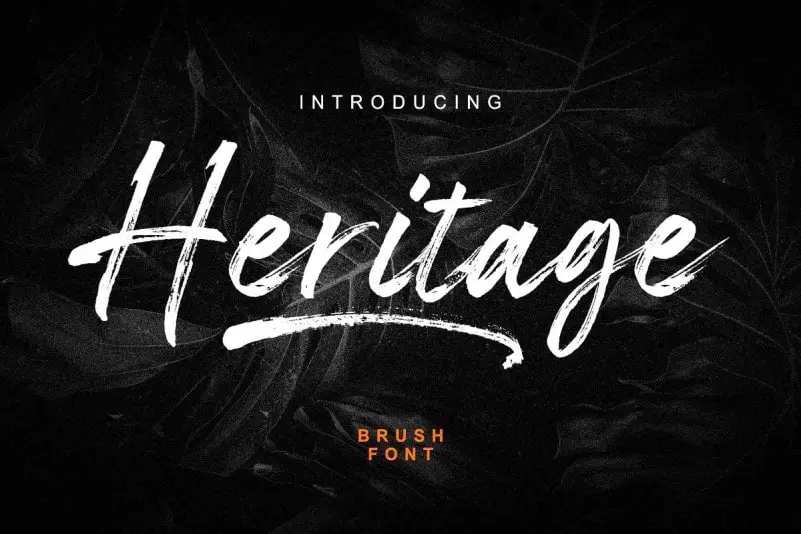
Heritage Brush Font – Download Grátis
A Heritage Brush Font é uma elegante tipografia escrita a mão que combina a facilidade dos traços de uma caneta com as curvas naturais e suavidades do estilo à mão. Seu design, criado por Hanzel Studio, traz um toque moderno e atrativo para qualquer projeto. Com suas linhas robustas, curveadas e determinadas, esta fonte casual é perfeita para quem busca uma adesão única e singular aos seus projetos. Ideal para criar um projeto que seja tanto clássico quanto contemporâneo, a Heritage Brush Font se destaca como uma opção versátil com uma ampla variedade de letras disponíveis para moldar sua criação no seu próprio estilo único.